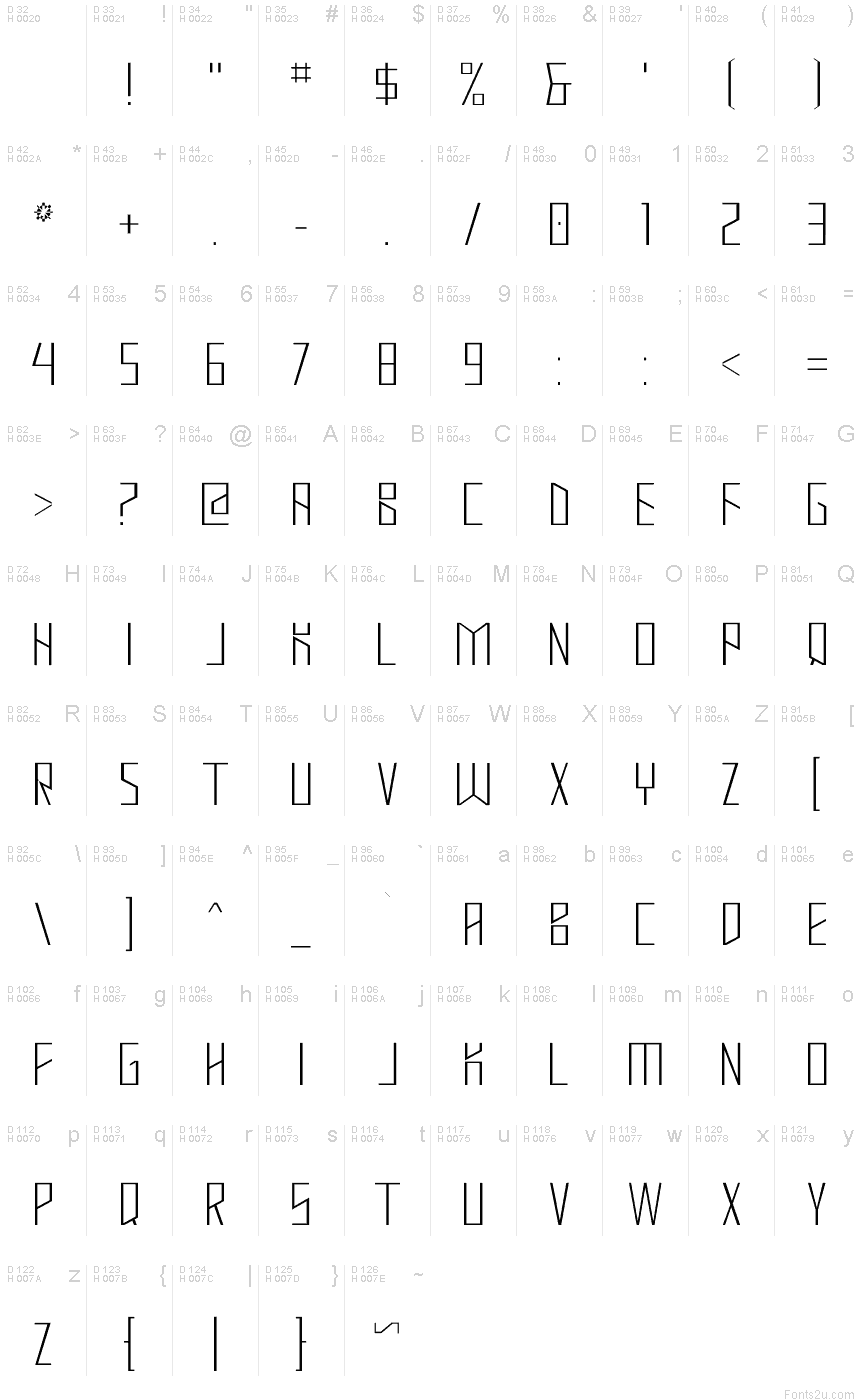
Mastodon Hairline od Apostrophic Laboratories to darmowy techniczny krój typu display, wyróżniający się wysokimi, prostokątnymi sylwetkami, kanciastymi krawędziami zewnętrznymi i ostrymi, ukośnymi cięciami, które przełamują surową geometrię siatki. Powtarzalny układ nadaje literom mechaniczny rytm, w którym każdy kształt wydaje się zredukowany do prostych odcinków, zamiast być wygładzonym w typowym stylu sci-fi.
Krój ten posiada odpowiednią wyrazistość do nagłówków w grach, ulotek muzyki elektronicznej, tytułów na plakatach, projektów logotypów oraz brandingu w stylu interfejsów. Dzięki wąskim, pionowym i wyraźnie segmentowanym kształtom, Mastodon Hairline dodaje ostrości krótkim nazwom i hasłom, gdy projekt wymaga syntetycznego, konstruktywnego wyglądu, zamiast neutralnego kroju display.
Mastodon Hairline